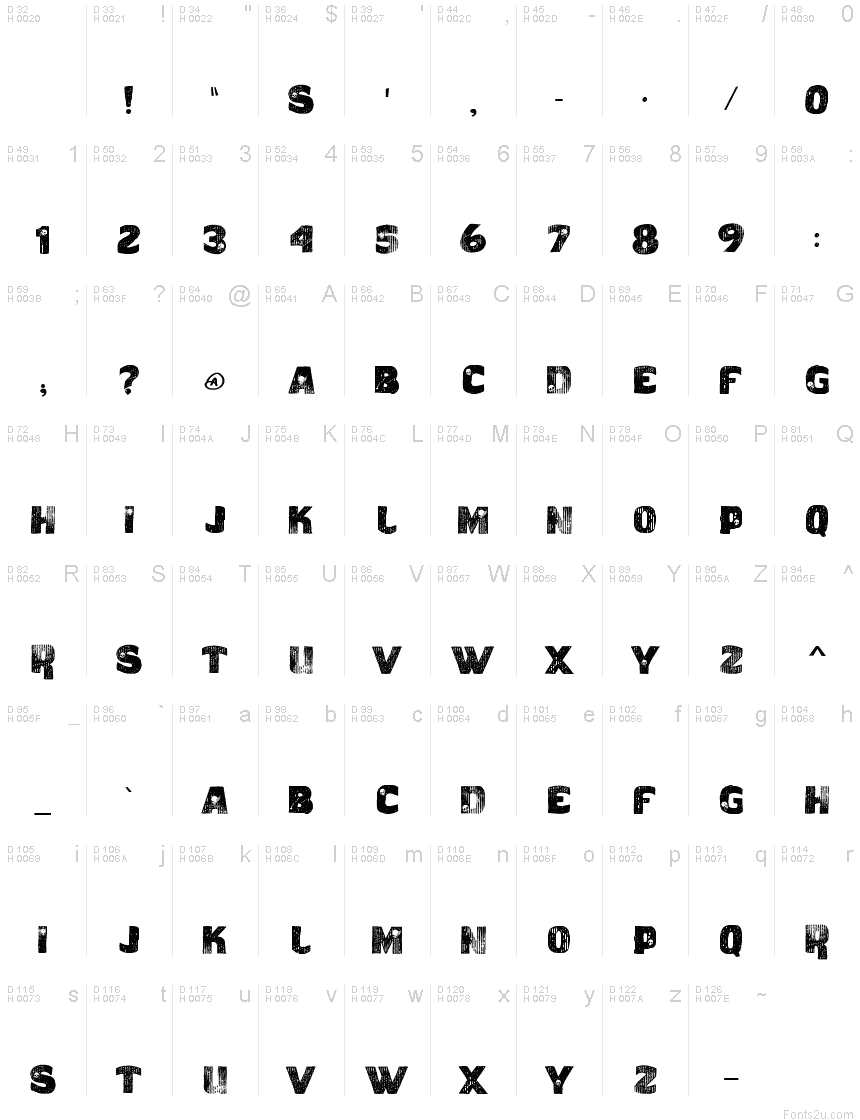
VTKS Caveirada von Douglas Vitkauskas ist eine kostenlose, zerfurchte Horror-Display-Schrift mit klobigen Großbuchstaben, die wirken, als wären sie aus abgenutztem Stein gemeißelt und mit Plakatfarbe bespritzt. Die Buchstaben wirken schwer und ramponiert, voller kleiner Narben, rauer Kanten und Totenkopf-Details, die die Stimmung eher in Richtung Pulp-Horror als in reinen Grunge lenken.
Sie passt perfekt zu Metal-Flyern, Halloween-Postern, Tattoo-Studio-Branding, Fanzine-Covern und Titelschildern, bei denen die Textur einen Teil der Geschichte erzählt. Als kostenloser Font eignet sie sich auch hervorragend für kurze Schlagzeilen, Bandlogos und Initialen im Monogramm-Stil, da das Totenkopf-Motiv und die distressed Füllung schon wenigen Buchstaben eine ganze Szenerie verleihen.